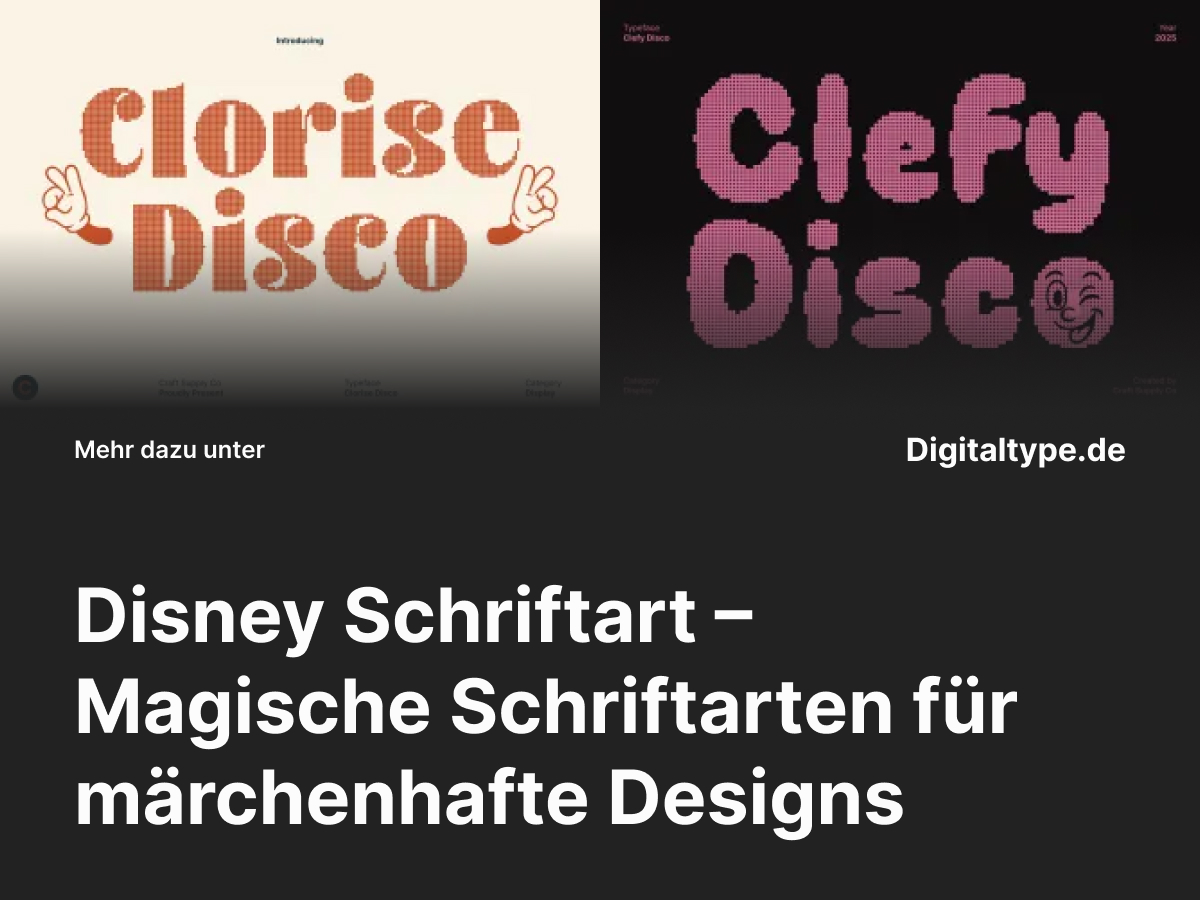
Du liebst die verspielte Magie der Disney-Welt? Dann ist eine Disney Schriftart genau das Richtige für dich!
Ob für kreative Projekte, Einladungen, Social Media oder Logos – diese Schriften verleihen deinem Design eine Prise Märchen und Nostalgie.
In diesem Artikel stellen wir dir wunderschöne Disney-inspirierte Fonts vor, die du sofort verwenden kannst.
Was ist eine Disney Schriftart?
Eine Disney Schriftart erinnert an den typischen Stil, den man aus Filmen, Freizeitparks und Logos kennt:
verspielte Buchstaben, sanfte Rundungen und ein Hauch von Magie.
Diese Schriftarten wecken Emotionen – perfekt für Designs, die Freude, Fantasie und Kindheitserinnerungen ausdrücken sollen.
Wo kann man Disney Schriftarten verwenden?
- 1. Kindergeburtstage & Einladungen: Ideal für märchenhafte Geburtstagskarten oder Poster.
- 2. Social Media & Branding: Hebe dein Profil mit einem unverwechselbaren, charmanten Schriftstil hervor.
- 3. DIY-Projekte: Perfekt für Scrapbooks, Aufkleber und kreative Bastelideen.
- 4. Web- & Printdesign: Nutze Disney Fonts, um deinem Layout Leben einzuhauchen.
Die 6 besten Disney Schriftarten Alternativen
Hier findest du sechs magische Disney Schriftart Alternativen, die den unverwechselbaren Charme und die Verspieltheit von Disney widerspiegeln:
1. Clorise Disco
Clorise Disco bringt bunte Energie und fröhliche Formen in jedes Design.
Ideal für Kinderprojekte, Poster und kreative Social Media Grafiken.
2. Clefy Disco
Clefy Disco vereint Retro-Stimmung mit Disney-ähnlicher Lebendigkeit.
Perfekt für Logos, Event-Designs und animierte Grafiken.
3. CS Micah Whimsical Font
CS Micah ist verspielt, charmant und ideal für Designs, die Spaß und Kreativität ausdrücken sollen.
Eine perfekte Wahl für Disney-inspirierte Projekte.
4. CS Maxine Playful Handwritten Font
CS Maxine bringt handschriftliche Energie und Verspieltheit.
Ideal für kreative Social Media Grafiken, Markenidentität oder Einladungskarten.
5. CS Chimera Stamp
CS Chimera hat einen charmanten Vintage-Stil mit kräftigen Buchstaben.
Perfekt für Retro-Disney-Fans oder nostalgische Designs.
6. CS Bimbo Messy Handwritten Font
CS Bimbo ist wild, verspielt und voller Persönlichkeit – genau wie klassische Disney-Abenteuer.
Ideal für kreative, lebendige Marken und Designprojekte.
Design-Tipps für Disney-Schriftarten
- 1. Verwende Farben mit Magie: Pastellfarben oder kräftige Töne passen perfekt zum Disney-Stil.
- 2. Kombiniere verspielte und klare Fonts: So entsteht ein harmonisches, professionelles Layout.
- 3. Achte auf Lesbarkeit: Auch bei verspielten Schriften sollte dein Text gut lesbar bleiben.
- 4. Nutze Disney-Schriften sparsam: Setze sie gezielt für Überschriften oder Highlights ein.
Fazit: Disney Schriftart für kreative Designs mit Zauber
Mit einer Disney Schriftart bringst du Magie in jedes Design – ob für Kinder, Marken oder Social Media.
Die vorgestellten Fonts sind ideale Alternativen, die Kreativität, Fantasie und Freude vereinen.
Wähle deinen Lieblingsfont, experimentiere mit Farben und erschaffe Designs, die Herzen verzaubern!